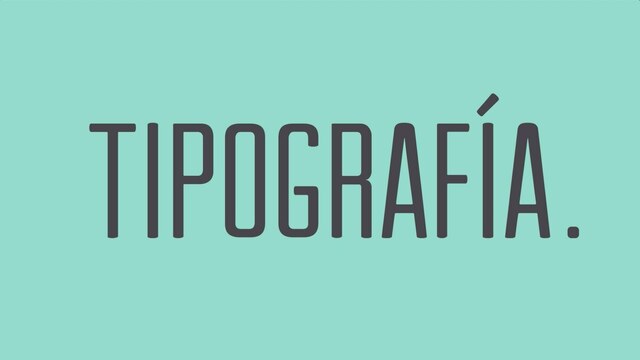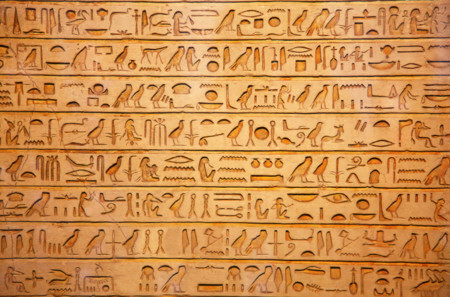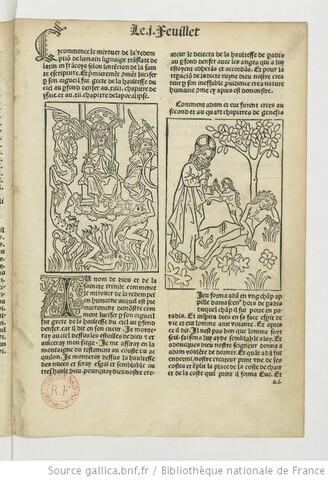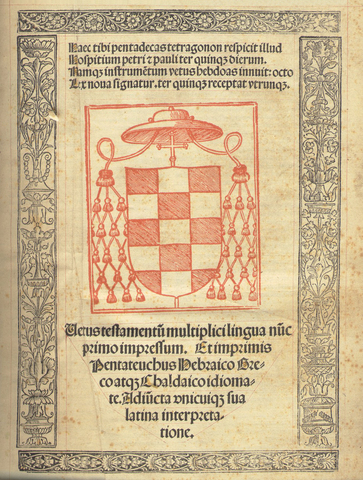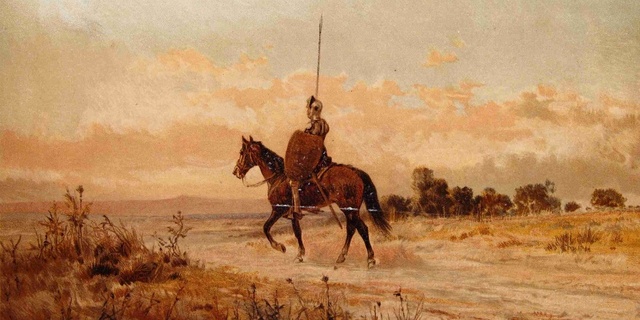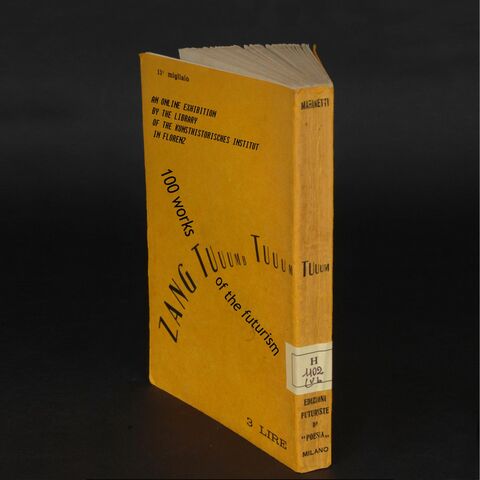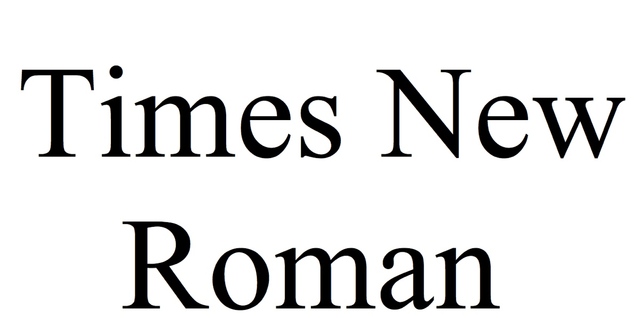
Fueron un sistema de escritura inventado por los antiguos egipcios. Esta cultura usó tres tipos de escritura, más esta fue la más relevante para ellos.
Desarrolló en Alemania una técnica para elaborar moldes de tipos que se utilizarían para la impresión de letras individuales.
Establecen la primera imprenta de Italia, en el Monasterio Benedicto de Subiaco.
Nicolás Jenson compone la obra "De Praeparatione Evangelica", obra que representa el crecimiento del diseño de tipos romanos.
Guillame Le Roy introdujo la imprenta en Lyon, Francia; cinco años después se imprime el libro "Le Mirover de la Rédemption", utilizando grabados en madera importados de Basilea.
Entre 1530-1585 las novedades tipográficas tienen su origen en Francia, en lo que se conoce como Edad de oro de la tipografía francesa y, aparte de ediciones a mano, muestra una creación de tipos bastante interesante.
El Rey Felipe ll de España comiso a Christophe Plantin para que trabajara en la "Biblia regia", la cual fue impresa en 5 lenguas: hebreo, griego, arameo, latín y siriaco.
Se imprimen los libros de bolsillo clásicos; Don Quijote de la Mancha, de Miguel de Cervantes. Los tipos que fueron utilizados fueron grabados por Christoffel van Dijck de Amsterdam.
Pierre Simon inició la estandarización del tamaño de los tipos al publicar su "Primera tabla de proporciones" en 1737
Ottomar Mengethaler inventó la linotipia, máquina usada en la composición tipográfica.
Tommaso Marinetti publicó su libro titulado "Zang Tumb Tumb" en 1914, donde ejemplifica su lema "la palabra en libertad" utilizando nuevas formas tipográficas, enfatizando el contenido del texto.
El Times New Roman se convirtió probablemente en el tipo más leído a mediados del siglo, fue diseñado por Stanley Morrison y Victor Lardent para el periódico estadounidense The Times; está inspirado en un tipo de Platin del siglo XVlll y se publico en 1932.